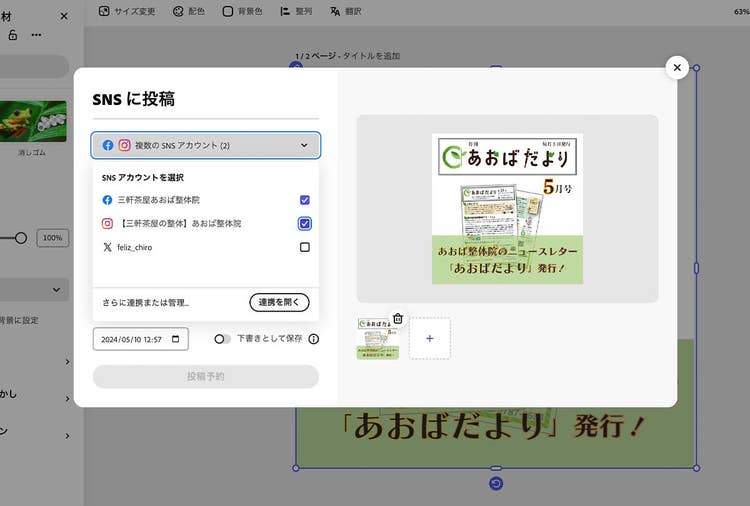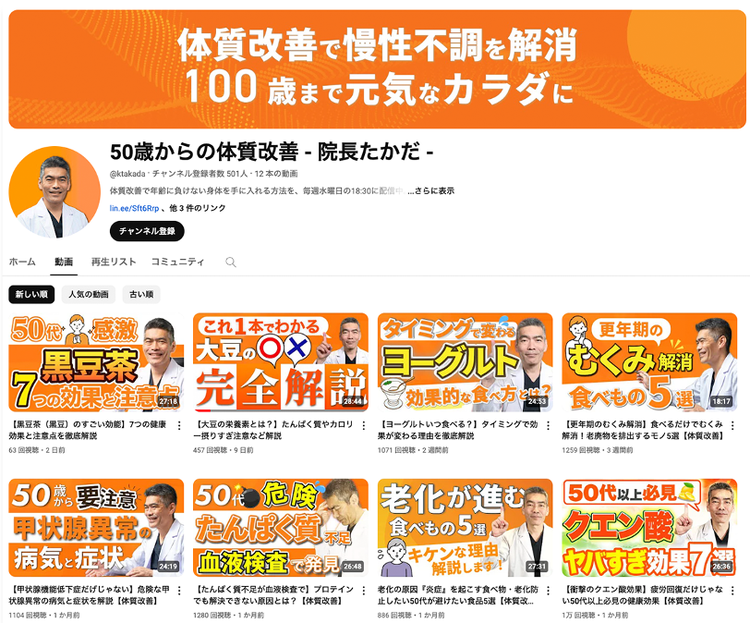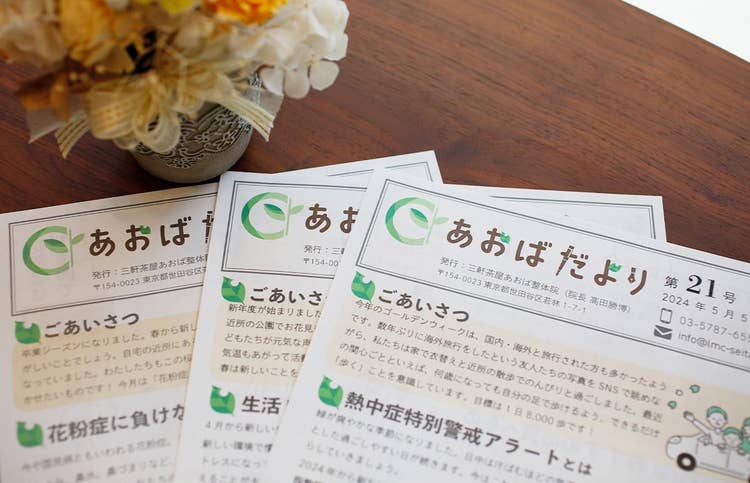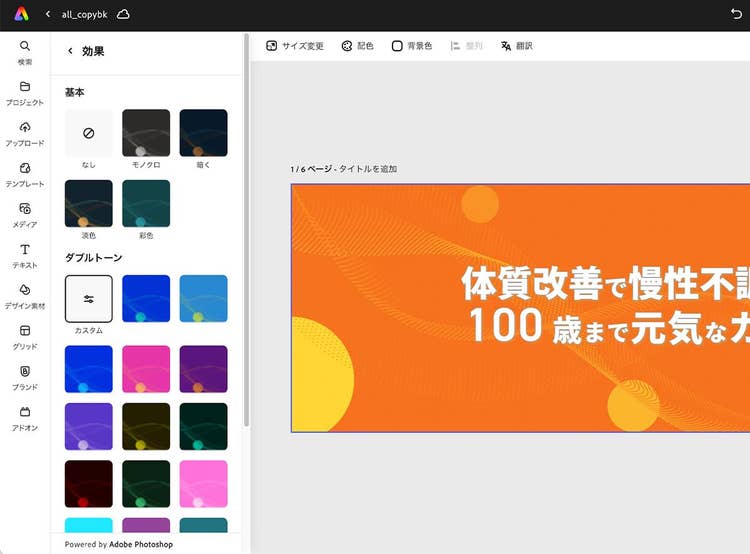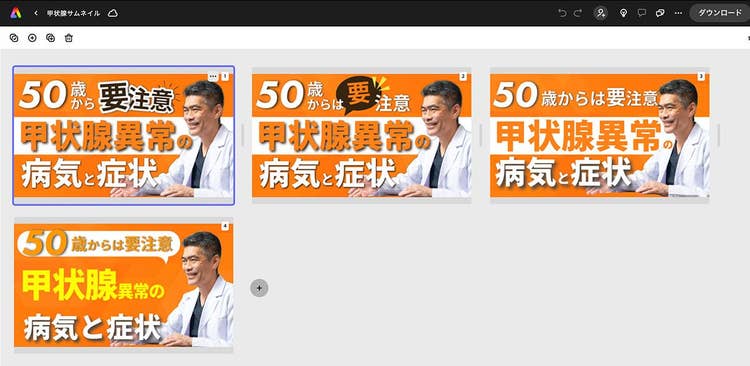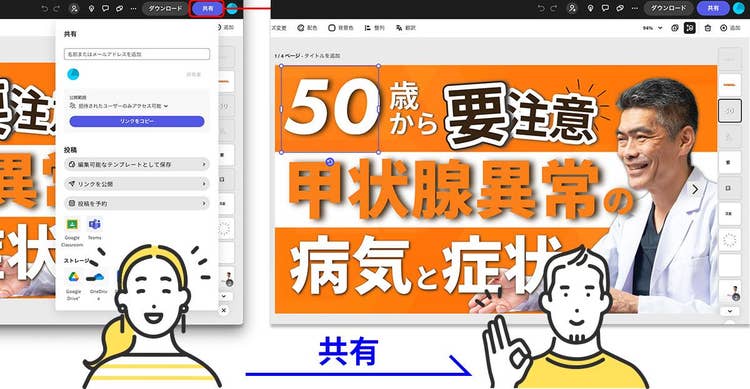
より魅力的な情報発信のためにデザインDIY
東京・三軒茶屋にある「三軒茶屋あおば整体院」は、web、blog、動画のようなオンラインメディアから、ニュースレターのようなペーパーメディアまで、さまざまな媒体を駆使して情報を発信しています。その制作を支えているのがアドビのクリエイティブツールです。一体、どのような経緯で自分たちでコンテンツを作り、発信していくようになったのでしょうか。副院長の長谷川知美さんにお話を伺いました。
「2019年に三軒茶屋あおば整体院がオープンした際、業者にwebサイト制作を依頼したのですが、その時のwebサイトは自由にアレンジできるつくりではありませんでした。その後、伝えたいことをきちんと伝えられるように、自分たちの手でリニューアルしたのが今のwebサイトです。
施術を受けたことのない方の中には、整体が何をするところなのかわからない、何をされるのかわからないと不安をお持ちの方もいらっしゃいます。そうした方が安心して来院いただけるように、さまざまなかたちで情報発信を続けています。
今はニュースレターやYouTube動画にも力を入れていて、ニュースレターにはAdobe Illustratorを、動画編集にはAdobe Premiereを使っているほか、デザインツールとしてAdobe Expressを利用しています」
▲Illustratorで
すばやく手軽にデザインできるAdobe Express
Webに掲載するバナーやYouTubeサムネイルなど、コンテンツ制作には多くのデザインが必要です。長谷川さんが現在画像制作のメインツールとして使っているのが、Adobe Express。その出会いはどのようなものだったのでしょうか。
「Adobe Expressを使うようになったのは、パソコンを使って作業をしている時に、ふと目に『Adobe Express』という文字に目がとまって。なんだろうと思って触り始めたのがきっかけです」
▲施術の
「Webサイトを作りはじめた頃は、Adobe Expressではなく、別のオンラインデザインツールでバナーや画像を作っていましたが、テキストのサイズを混在させるような細かいコントロールができなかったり、思うようにデザインできませんでした。
無料アプリだから仕方ない……と半ばあきらめていましたが、同じ無料アプリのAdobe Expressを使ってみたら、Illustratorでテキストを扱う時と同じようにデザインができて。それからデザインツールをAdobe Expressに切り替えたんです。
自分でこういうデザインを作ろうと決めてから作業をすることが多いので、たくさん用意されているテンプレートをそのまま使うことはほとんどないのですが、データのつくりや使っている機能を調べるためにテンプレートを開くことはあります。気になるデザイン、表現があった時、フォントやパーツの組み合わせ方がわかれば、自分のデザインに活用することができますから」
▲配色に
▲いくつもの
長谷川さんは、デザイン以外の部分でも、Adobe Expressを使うメリットを感じています。
「Adobe Expressは作ったデザインを見てもらう時にも便利なんです。
たとえば、Illustratorでデザインした場合、画像やPDFに書き出して相手に送るか、ノートパソコンごと持っていって、ファイルを開いた状態で見てもらう必要があったのですが、Adobe Expressなら共有ボタンからリンクを作成して送るだけで、相手に同じ状態で見てもらうことができます。ソフトがインストールされていないから開けない……そんな心配もいりません」
Illustratorのようなプロ向けデザインツールを使えるのに、なぜAdobe Expressを使うのか。そこには、長谷川さんならではの、明確な使い分けがありました。
「Illustratorだと細かい設定が必要だったり、細かいところにもこだわってしまったり……どうしても時間をかけてしまいがちです。YouTubeのサムネイルやBlogのバナーのように決まったサイズの画像を作る時には、Adobe Expressのほうが圧倒的に早く作れます。
とくにwebコンテンツはどんどん更新していく必要があるので、とにかく時間をかけず、手軽にデザインできるツールのほうがありがたいし、使いやすいんです」
▲Adobe Expressの
豊富なフォントでデザインに強さを
デザインツールをAdobe Expressに切り替えたことで、長谷川さんが感じるメリットはほかにもあります。それがAdobe Fontsの豊富なフォントです。
「日本語フォントを使ってサムネイルを作っていると数字だけ弱く感じることがよくあるんですね。そういう時は数字だけ別のフォントに変えたりしています。
フォントを探す時は、ブラウザでAdobe Fontsを開いて、ひとつひとつ欧文フォントをチェックしていくんです。イメージに合うフォントを見つけたらAdobe Expressに戻って、フォントを指定する……そんなふうに使っています。Adobe Expressからもフォントは探せるのですが、たくさんのフォントから目的のものを探すなら、Adobe ExpressのフォントメニューよりもAdobe Fontsのほうが見やすいんですよね。
以前のツールにはここまで豊富にフォントが揃っていなかったので、今は候補が多すぎて逆に探すのが大変なくらいです(笑)」
「Adobe Expressは、機能が限られている分、目につきやすいせいか、使い方がわからない、思ったようにデザインできないということがまったくありません。触っているうちに、自分が作りたかったものができあがっちゃう(笑)。それがとにかく楽しいんですよね」
豊富なテンプレートとフォントによって、すばやく高品質なデザインができるAdobe Express。「デザインが楽しい」という長谷川さんの言葉には、その魅力が凝縮されています。
▲ 週一
▲三軒茶屋あ